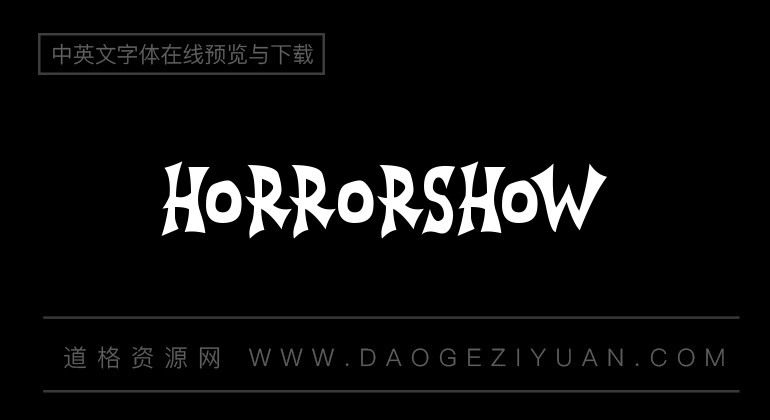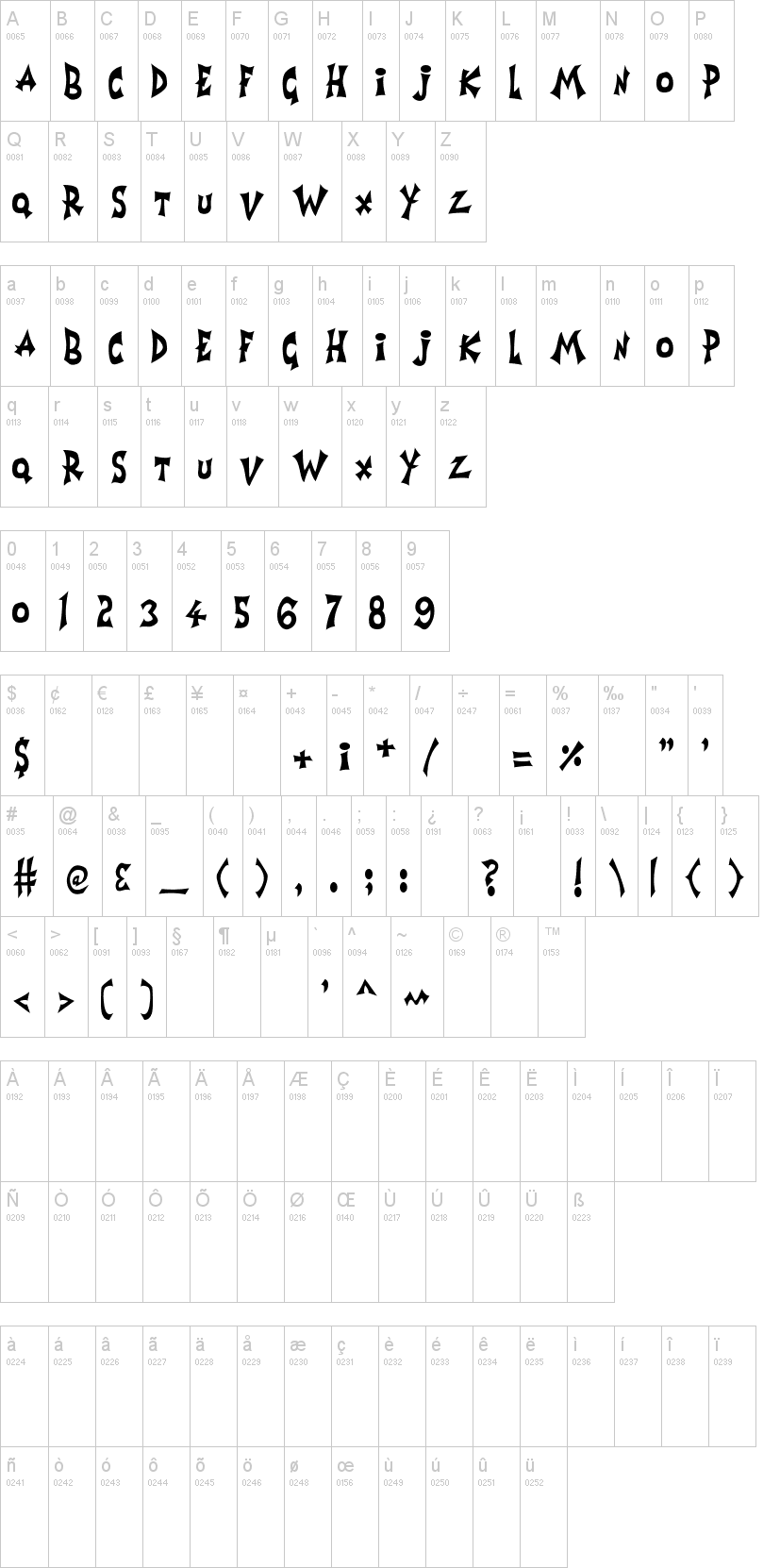
Horrorshow 是一款比较另类的字体,由字体设计师 Neil Summerour 于2006年设计。它拥有黑色、古老、粗犷的外观,可以用来创作恐怖、悬疑等主题的标题或文字。它有三种字体:Horrorshow Regular、Horrorshow Italic 和 Horrorshow Bold。Horrorshow Regular 字体有一种类似印刷品的细节,而 Horrorshow Bold 和 Horrorshow Italic 则更加抽象,更能表达出惊悚的气氛。内容介绍
Horrorshow是一款非常不错的手写艺术字体,具有很好的视觉感,适合于文化类的宣传设计、商业类品牌的广告和产品包装设计以及个性化文字排版等较多场景。